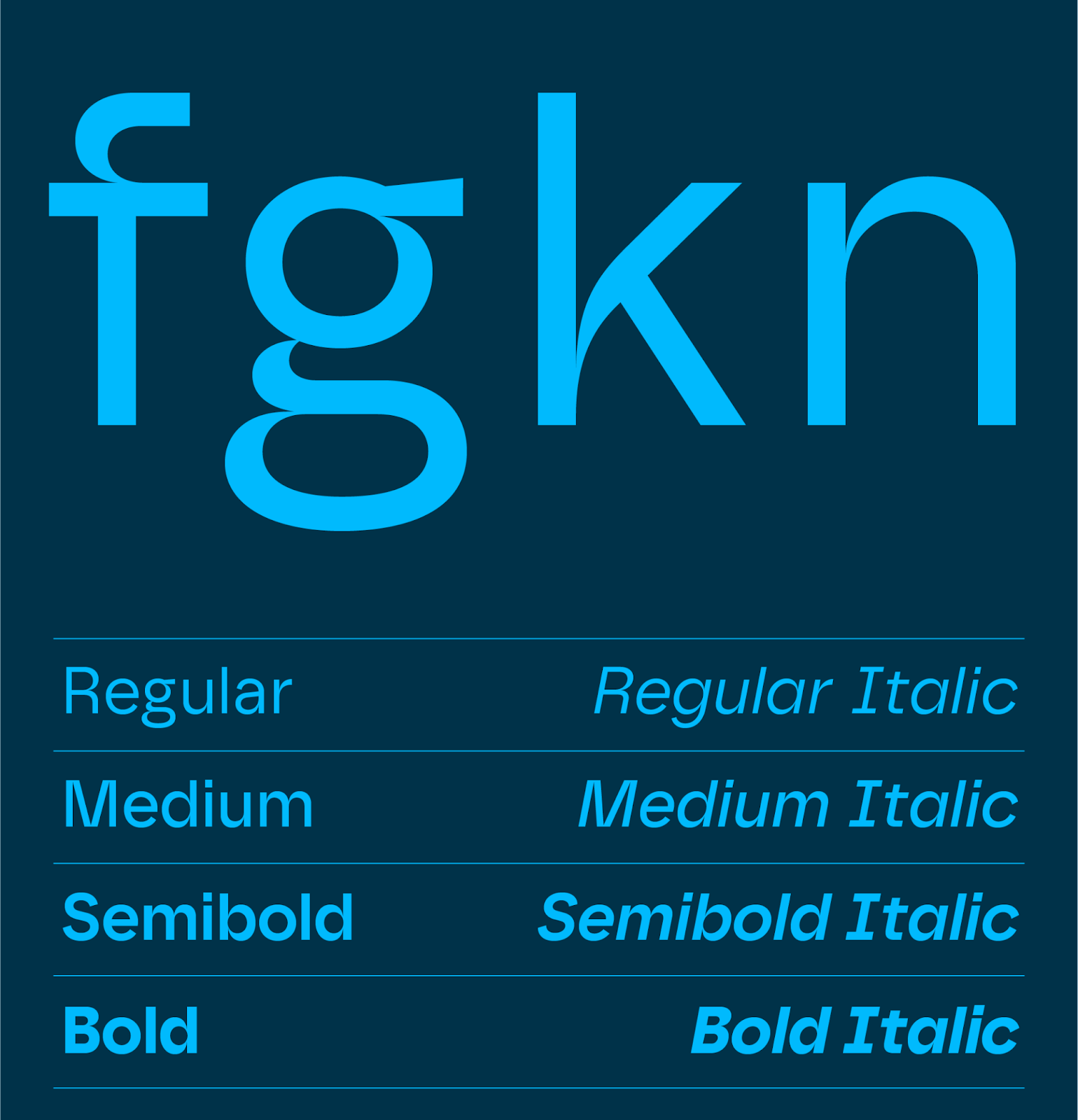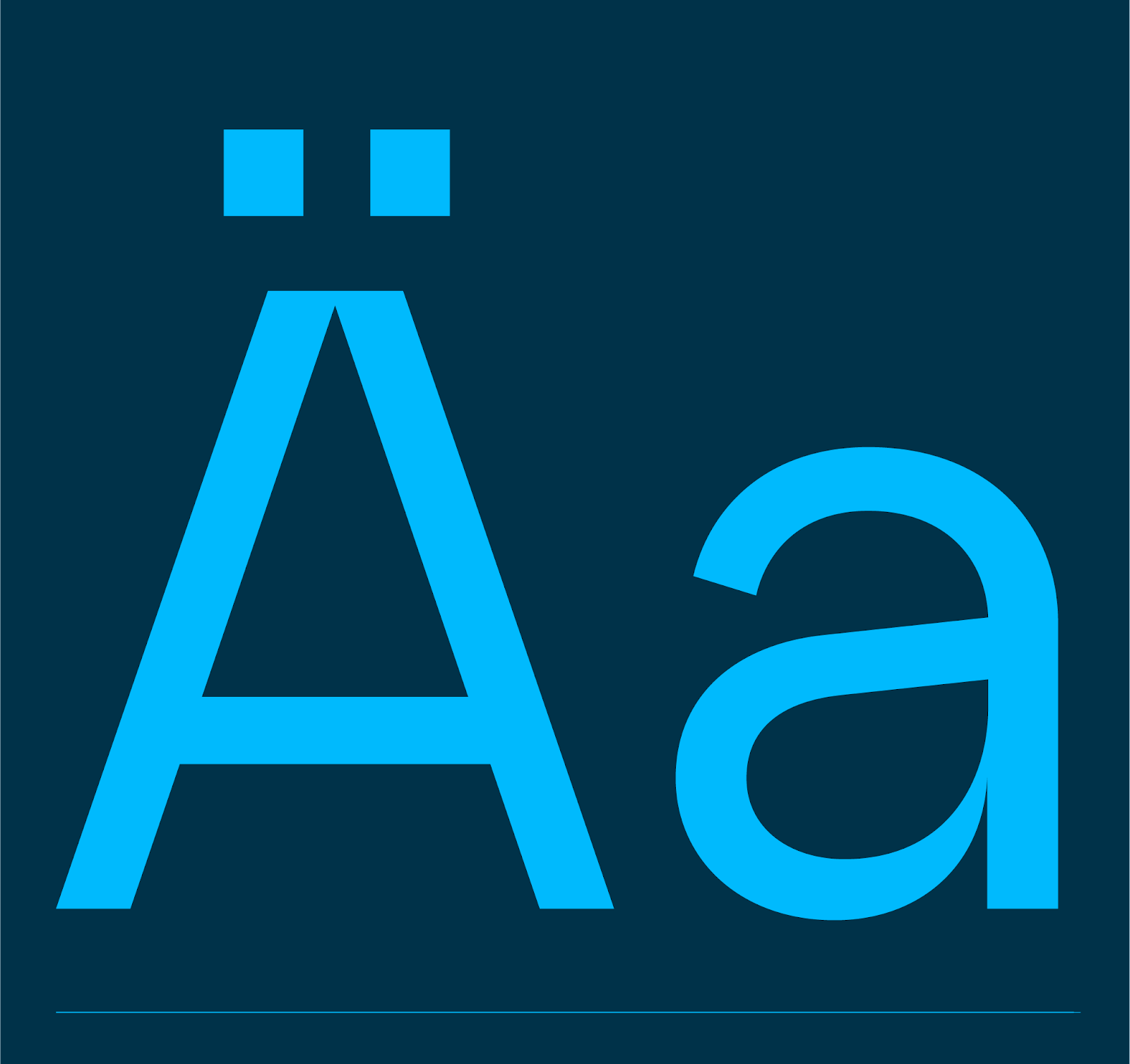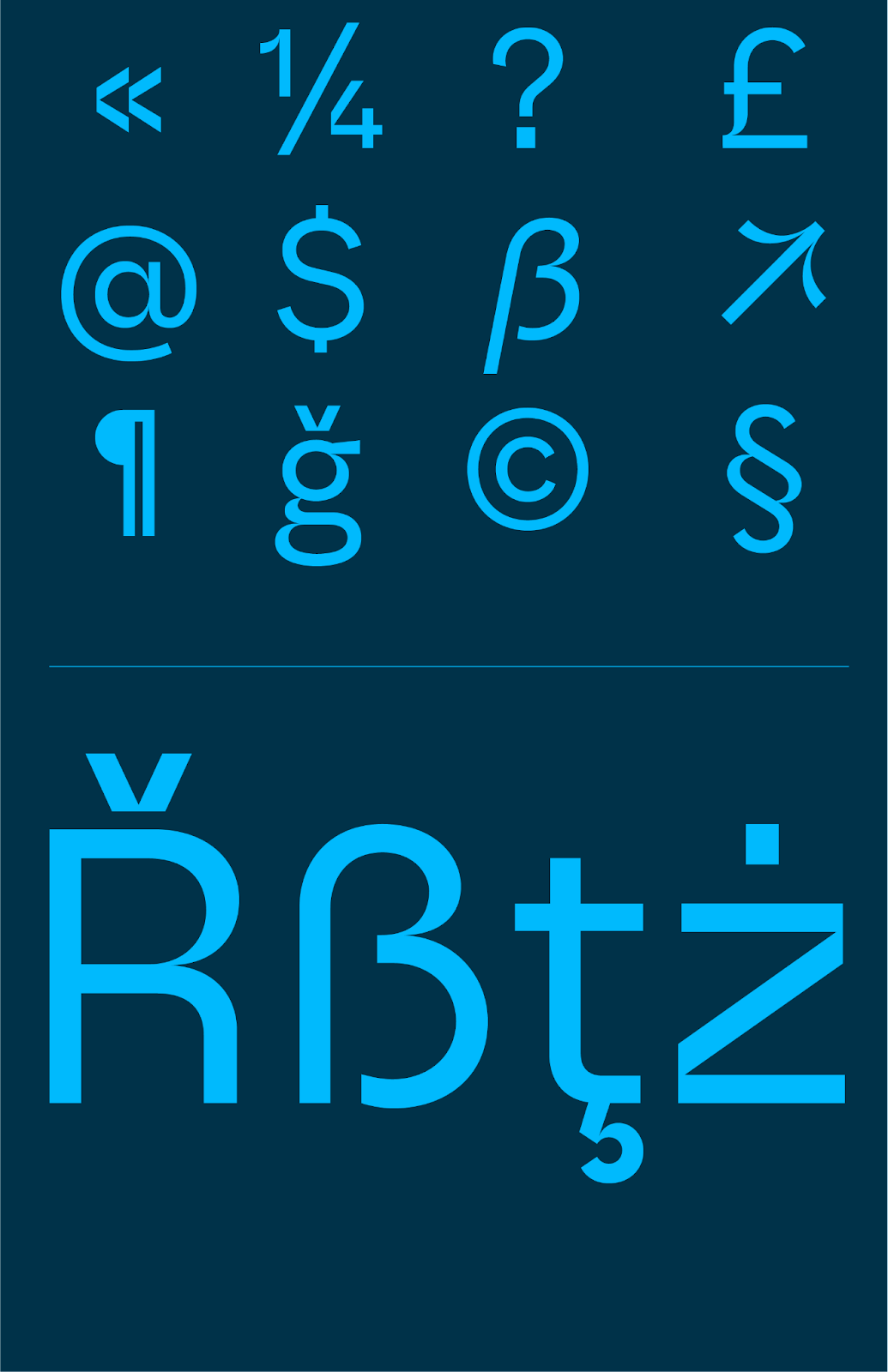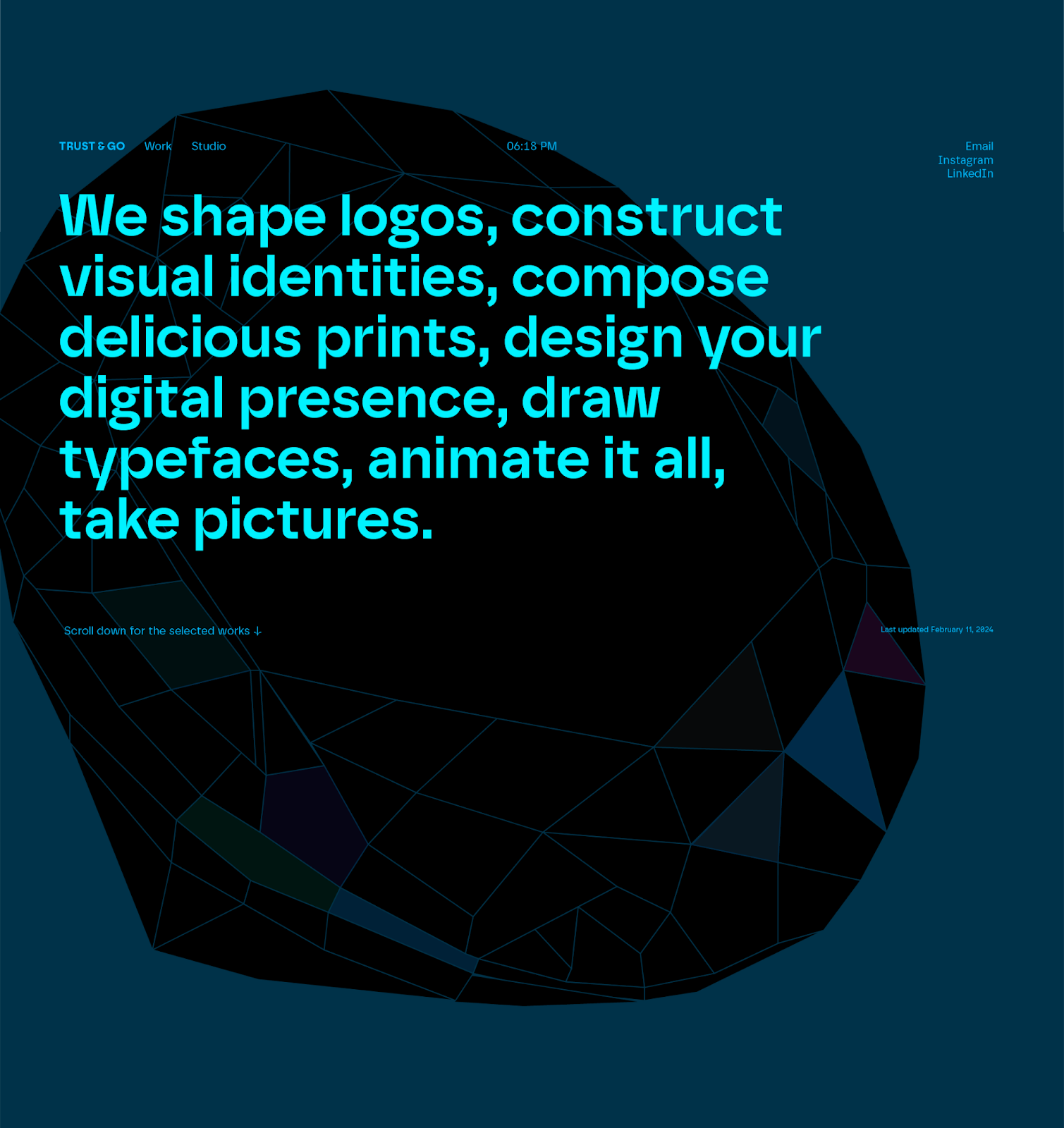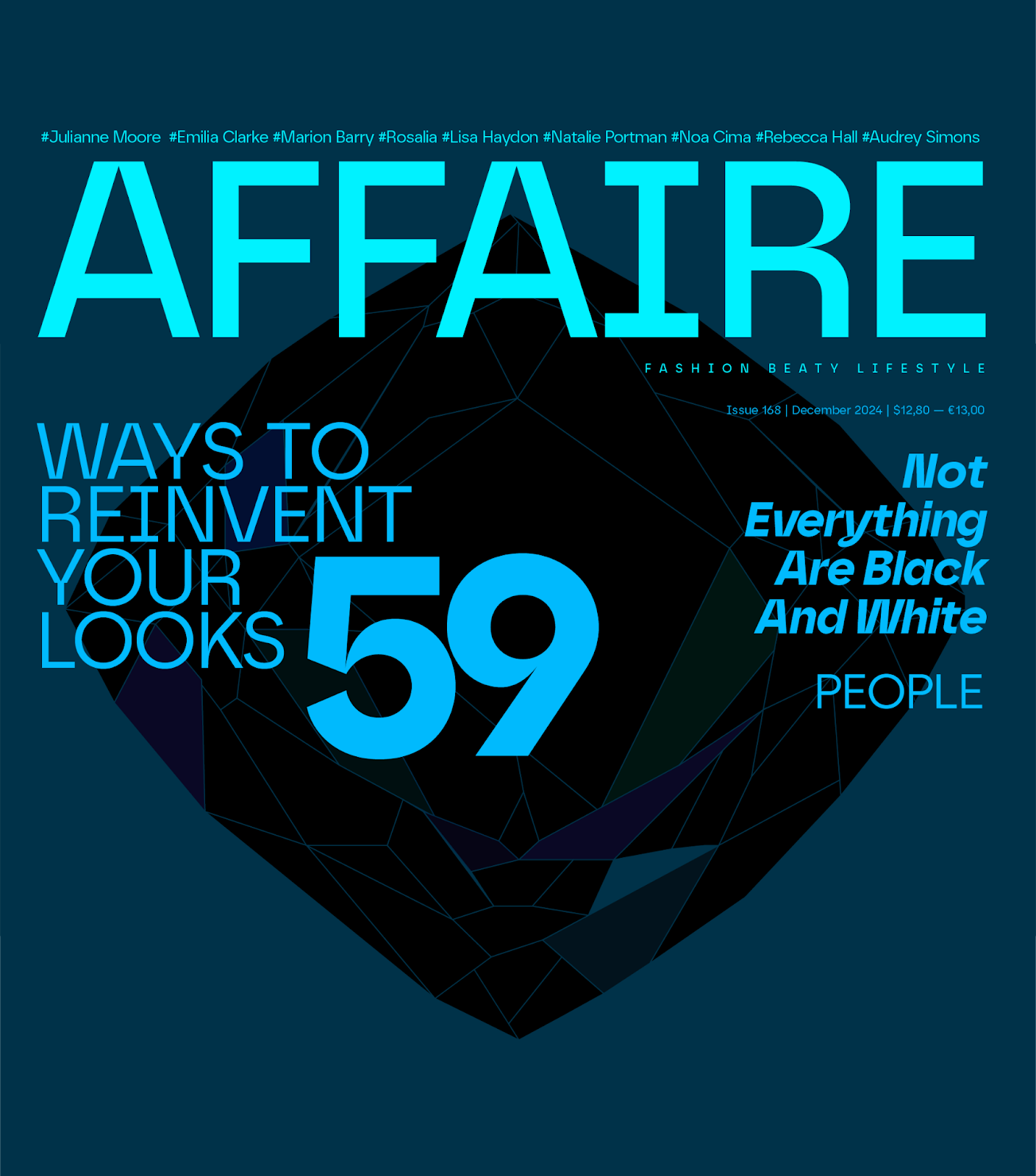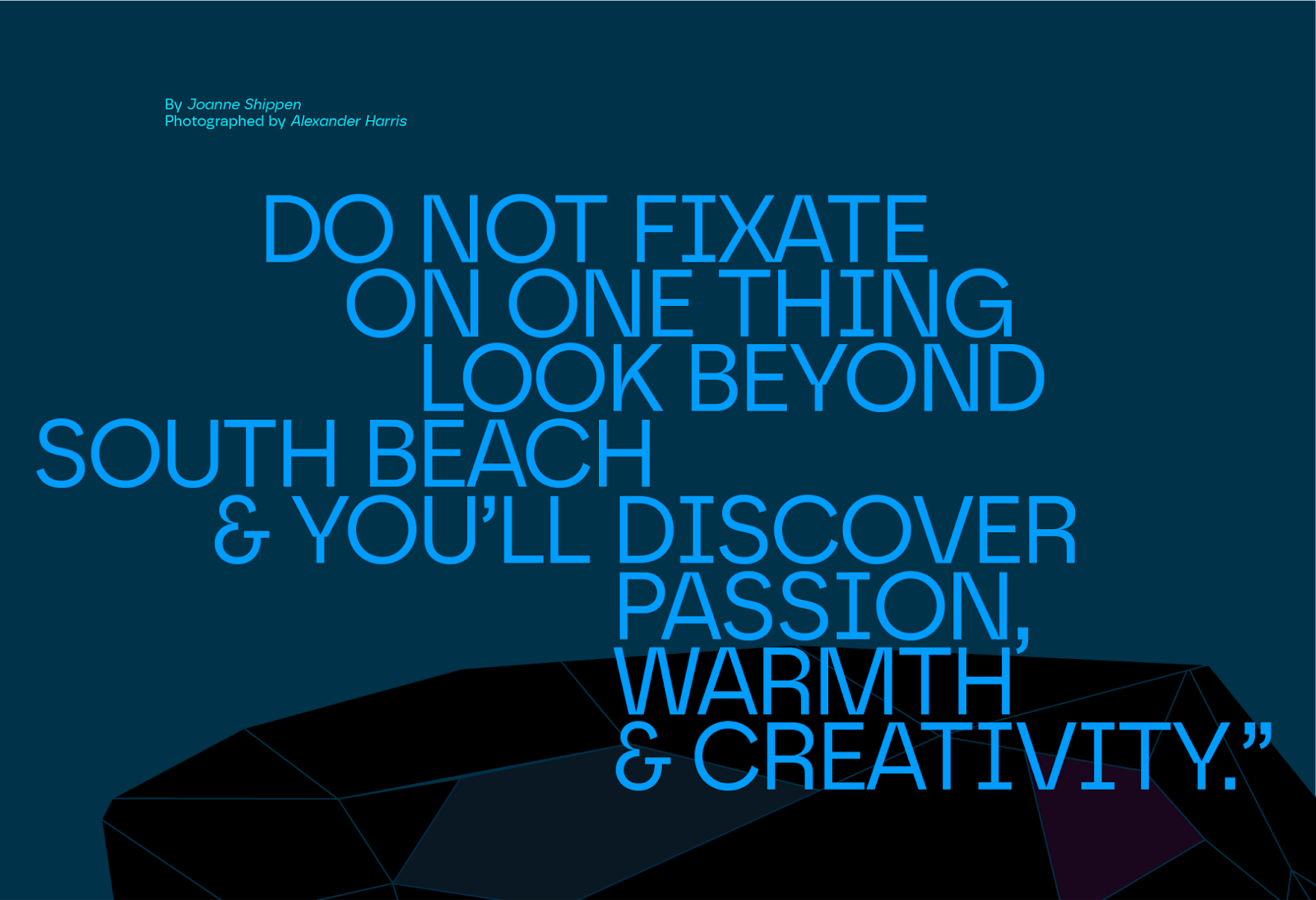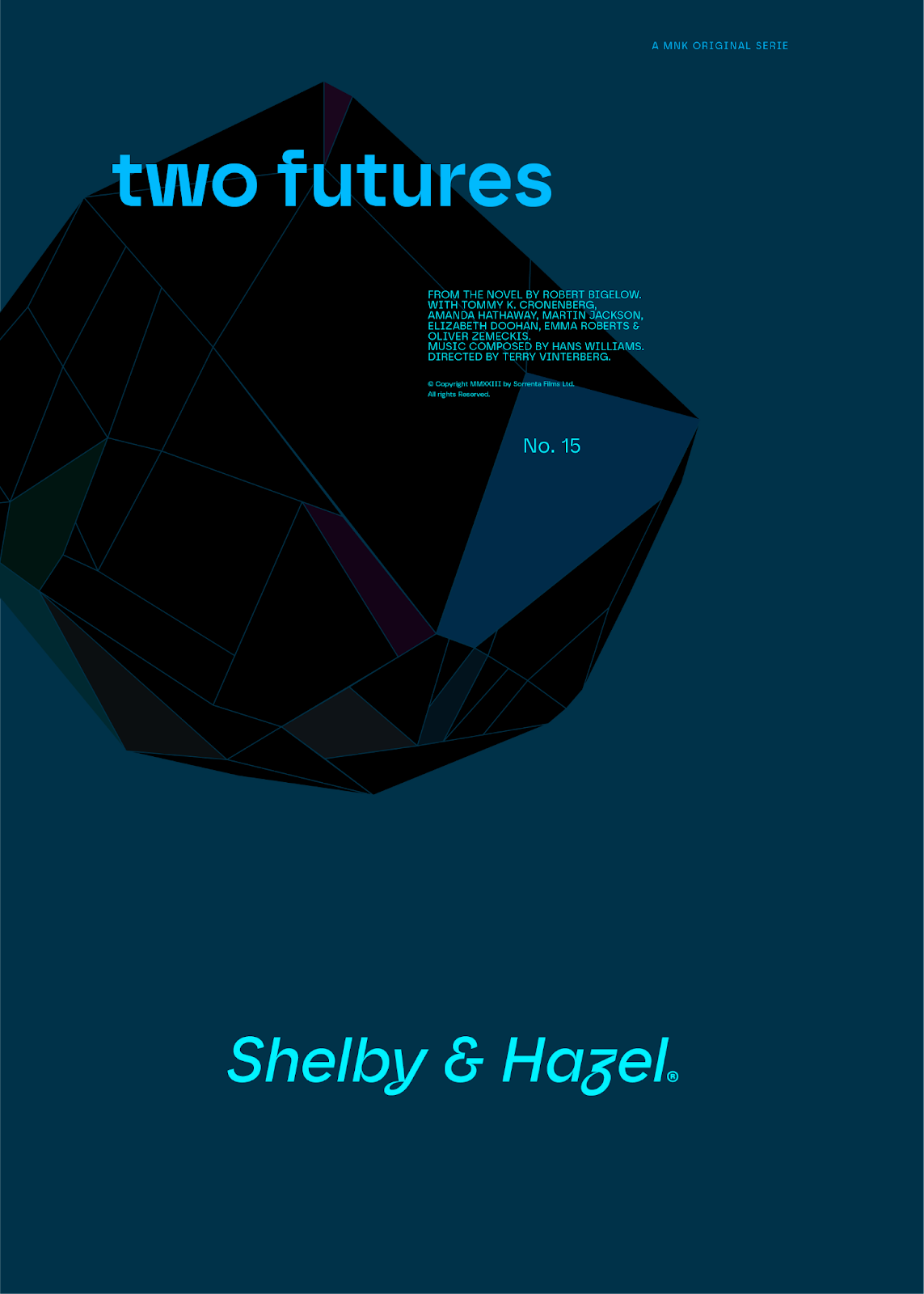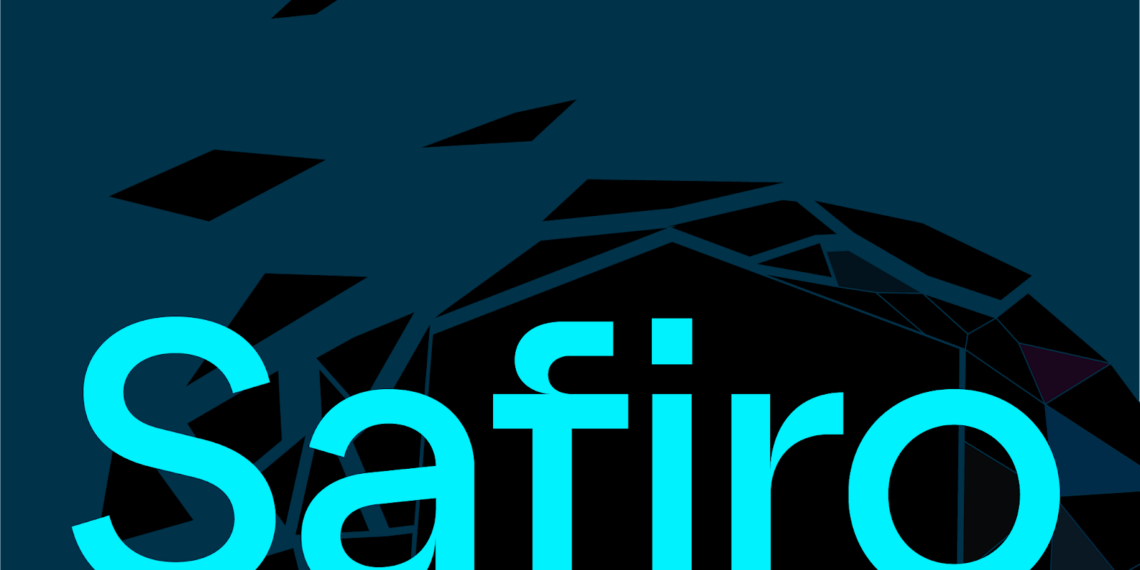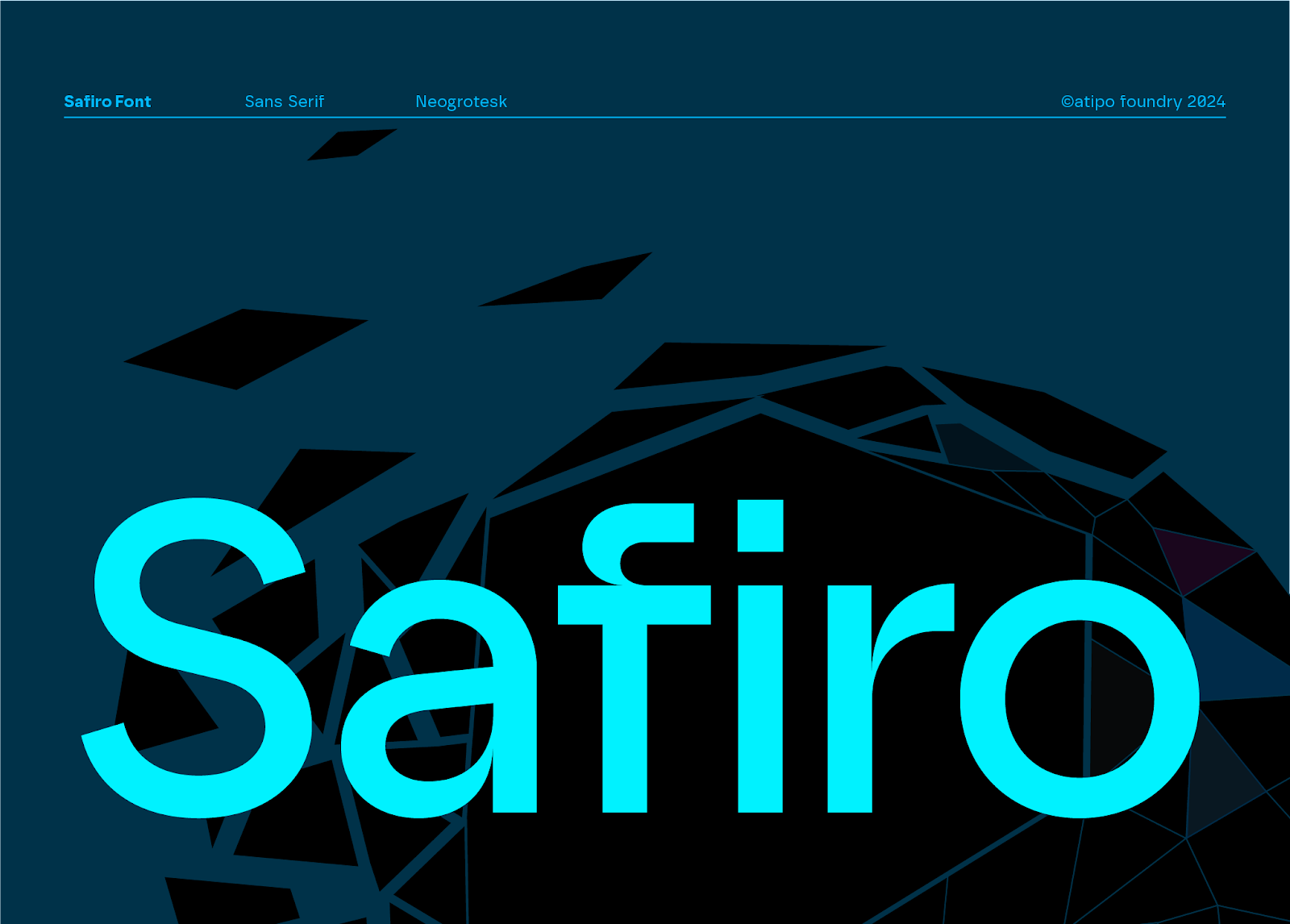
Entdecken Sie die Eleganz der Safiro-Schriftart, ein Meisterwerk im Schrift- und Typografiedesign, perfekt für Branding, Redaktion und Webdesign. Entdecken Sie ihren einzigartigen neogrotesken Stil.
In der sich ständig weiterentwickelnden Welt des Designs erweist sich die Safiro-Schriftart als herausragendes Beispiel dafür, wie Typografie das Branding und die visuelle Identität tiefgreifend beeinflussen kann. Entwickelt von der renommierten Schriftgießerei atipo®, ist Safiro nicht nur eine Schriftart; sie ist ein Zeugnis für die Kraft des Designs, wenn Kunst auf Präzision trifft.
Diese serifenlose Familie ist eine brillante Präsentation des neogrotesken Stils, der auf rationalistischen Prinzipien basiert, jedoch durch eine moderne Perspektive neu interpretiert wurde. Die Schöpfer haben die Proportionen jedes Buchstabens meisterhaft ausbalanciert und eine exquisite Mischung aus technischer Genauigkeit und ästhetischer Anmut erreicht. Dieses Gleichgewicht verleiht Safiro eine unverwechselbare Persönlichkeit und hebt sie im Bereich des Schriftdesigns hervor.
Eine der überzeugendsten Eigenschaften von Safiro ist ihr Strichkontrast, der Tiefe und Charakter verleiht, ohne das Design zu dominieren. Diese Subtilität stellt sicher, dass die Schriftart ihre Eleganz in verschiedenen Anwendungen behält, vom digitalen Bildschirm bis zur gedruckten Seite. Es ist diese Vielseitigkeit, die Safiro zu einer ausgezeichneten Wahl für eine Vielzahl von Projekten macht, einschließlich der Logoerstellung, Branding-Bemühungen, redaktionellen Layouts, Verpackungsdesigns und Webinterfaces.
Die Safiro-Familie ist beeindruckend umfangreich und bietet acht Gewichtsvarianten von Regular bis Bold. Diese Vielfalt an Gewichtsoptionen, kombiniert mit echten Kursiven, bietet Designern eine beispiellose Flexibilität. Ob beim Gestalten eines minimalistischen Logos oder einer dynamischen Webseite passt sich Safiro mühelos an und unterstreicht den Inhalt mit ihrem einzigartigen Charme.
In einer Welt, in der Marken danach streben, sich abzuheben, bietet Safiro eine Grundlage für die Schaffung von Identitäten, die Resonanz finden. Ihre einzigartige Mischung aus Eleganz und Funktionalität macht sie zu einem wertvollen Werkzeug im Arsenal eines Designers. Wenn wir die Möglichkeiten erkunden, die Safiro bietet, wird deutlich, dass diese Schriftart nicht nur darum geht, Wörter auf eine Seite zu bringen; es geht darum, Erlebnisse zu schaffen, die ansprechen und inspirieren.
Zusammenfassend ist Safiro mehr als nur eine Schriftart; sie ist ein Meilenstein im Schrift- und Typografiedesign, der zeigt, wie durchdachtes Design die Kommunikation in jedem Medium verbessern kann. Ihr Beitrag zur visuellen Sprache unserer Zeit wird zweifellos von Designern und Marken geschätzt werden, die einen bleibenden Eindruck hinterlassen wollen.